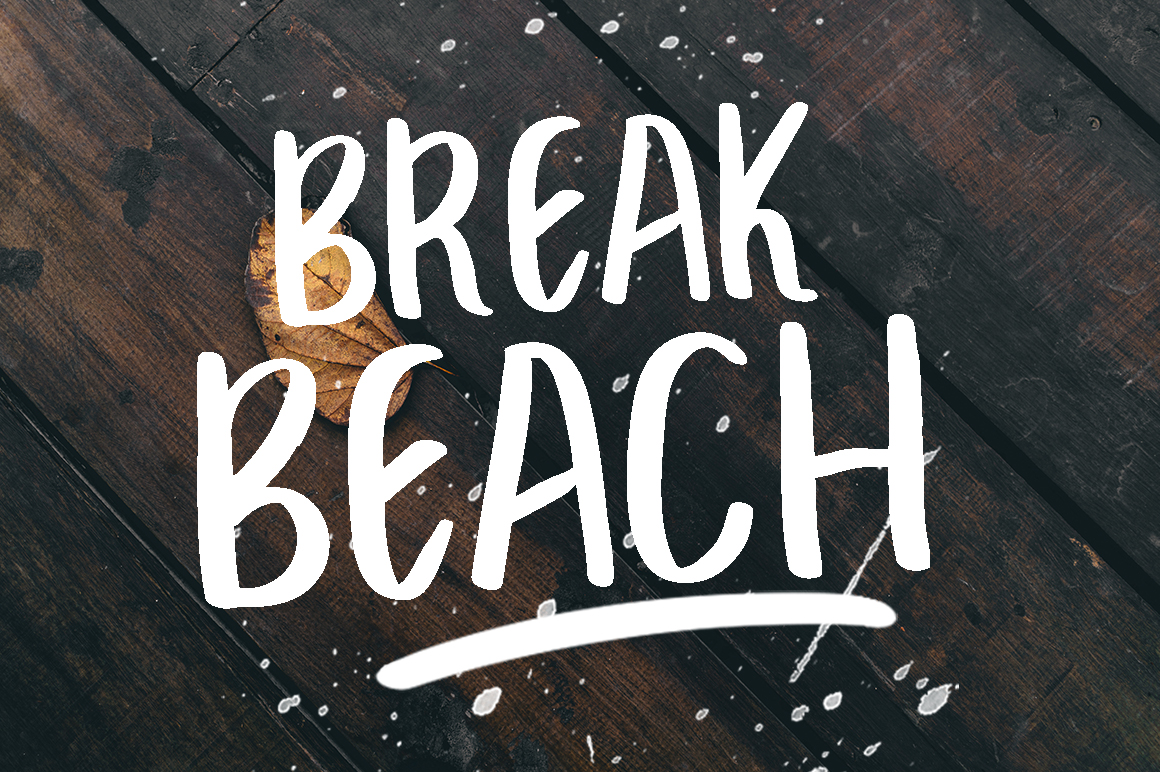
Break Beach
適切なデザイン要素を見つけるのは難しい場合がありますが、Break Beachは作品を即座に引き立てる優れたコレクションを提供します。
POD(オンデマンド印刷)製品、結婚式の招待状、またはソーシャルメディアのグラフィックを作成している場合でも、Break Beachは理想的です。